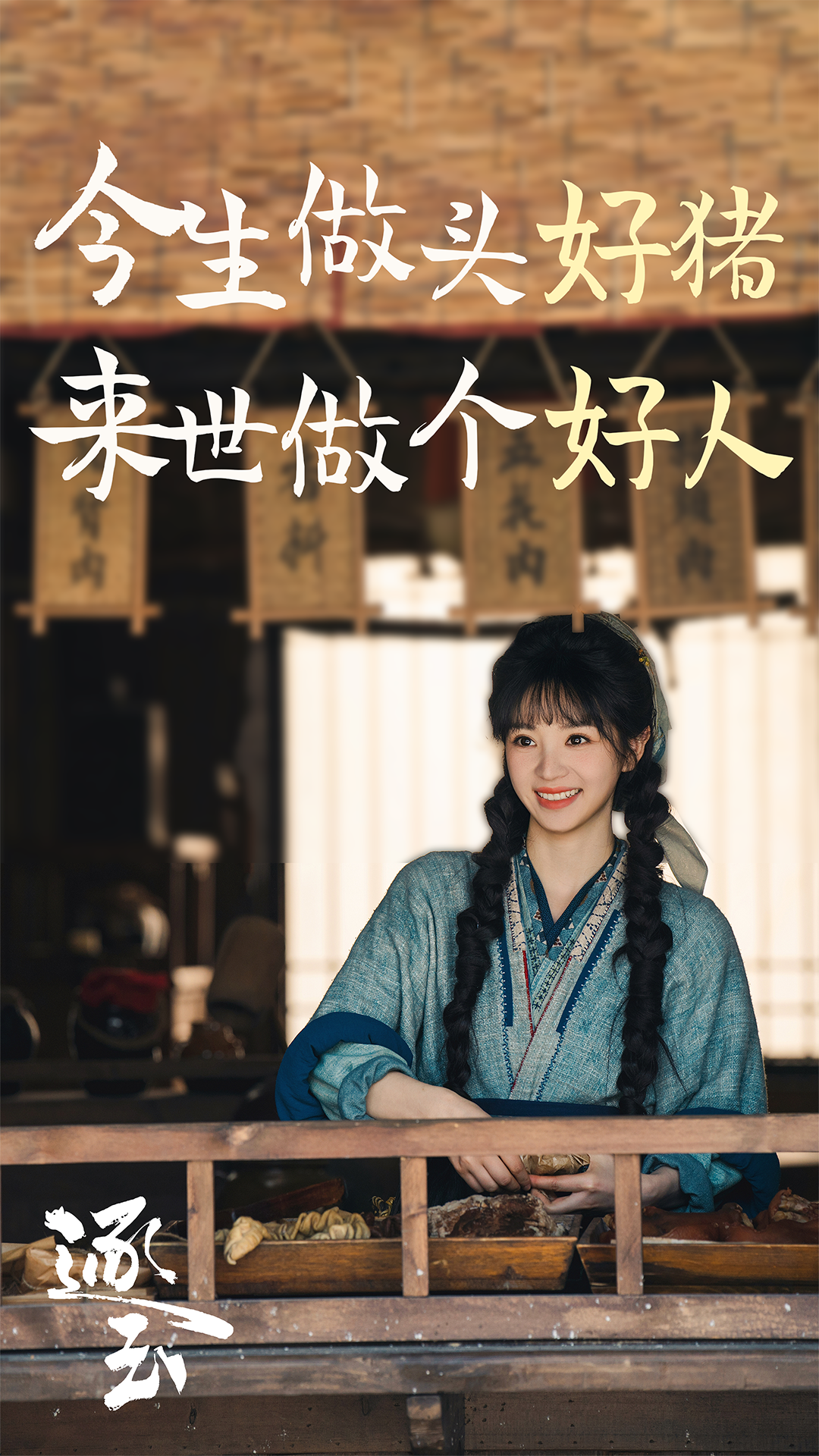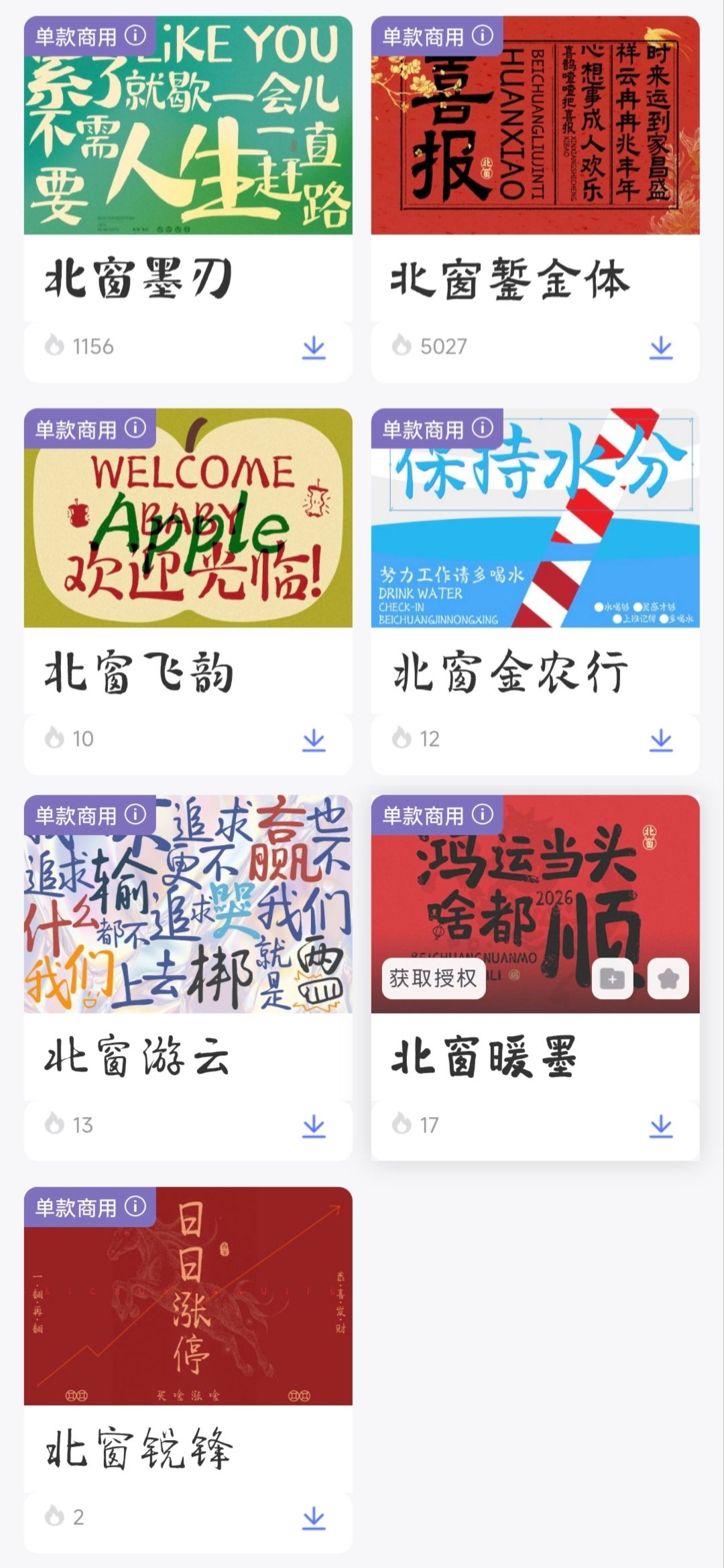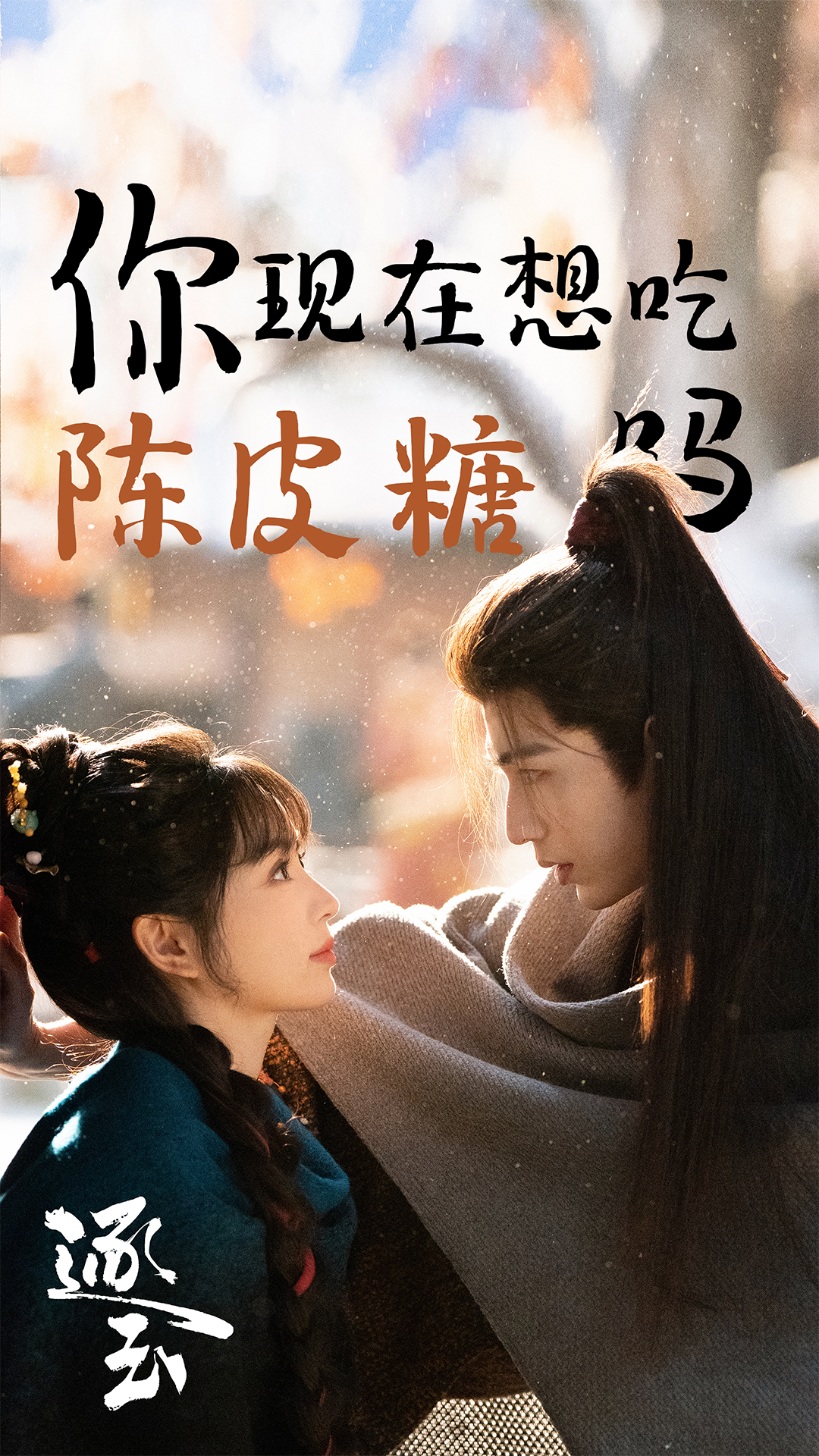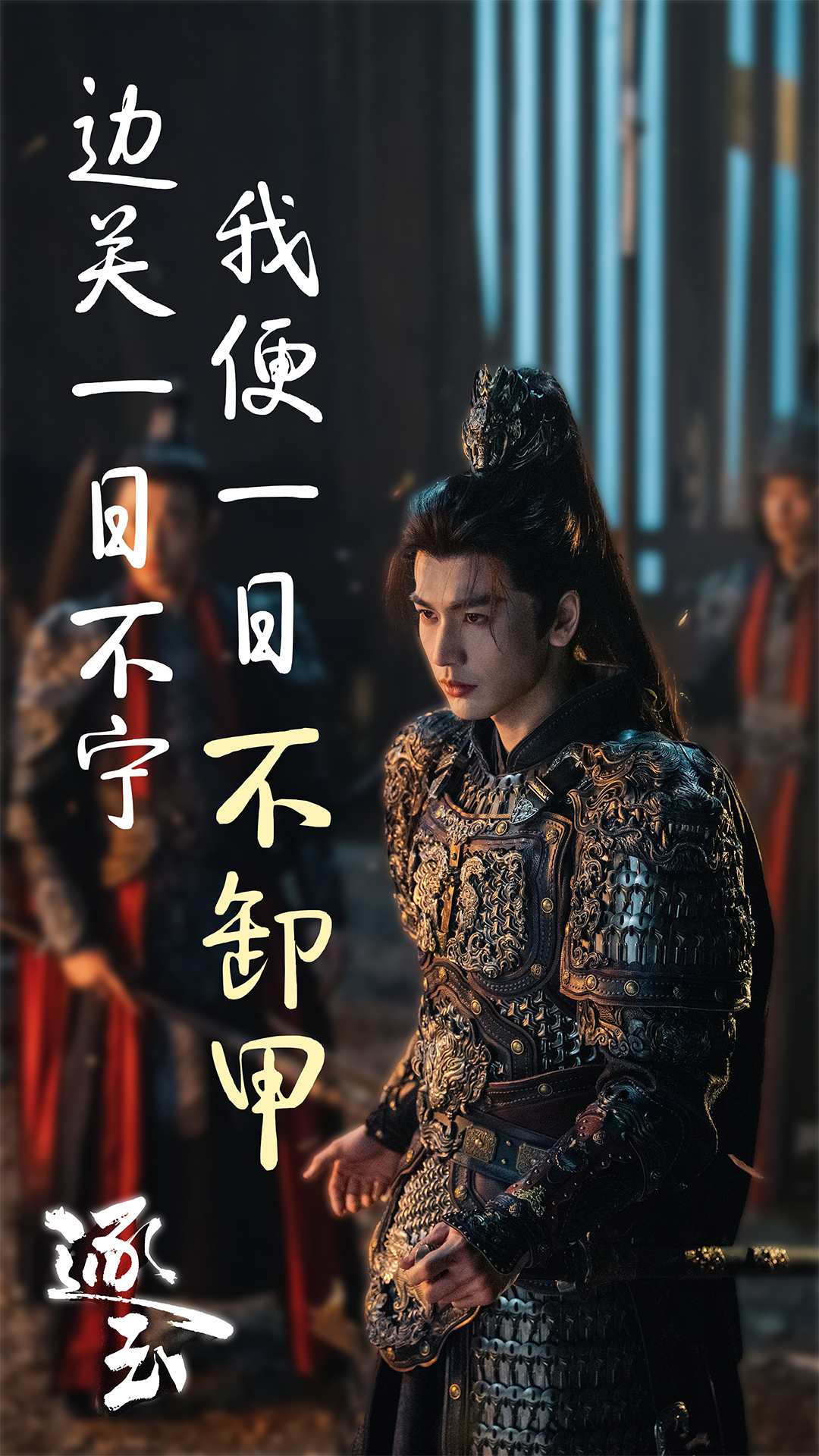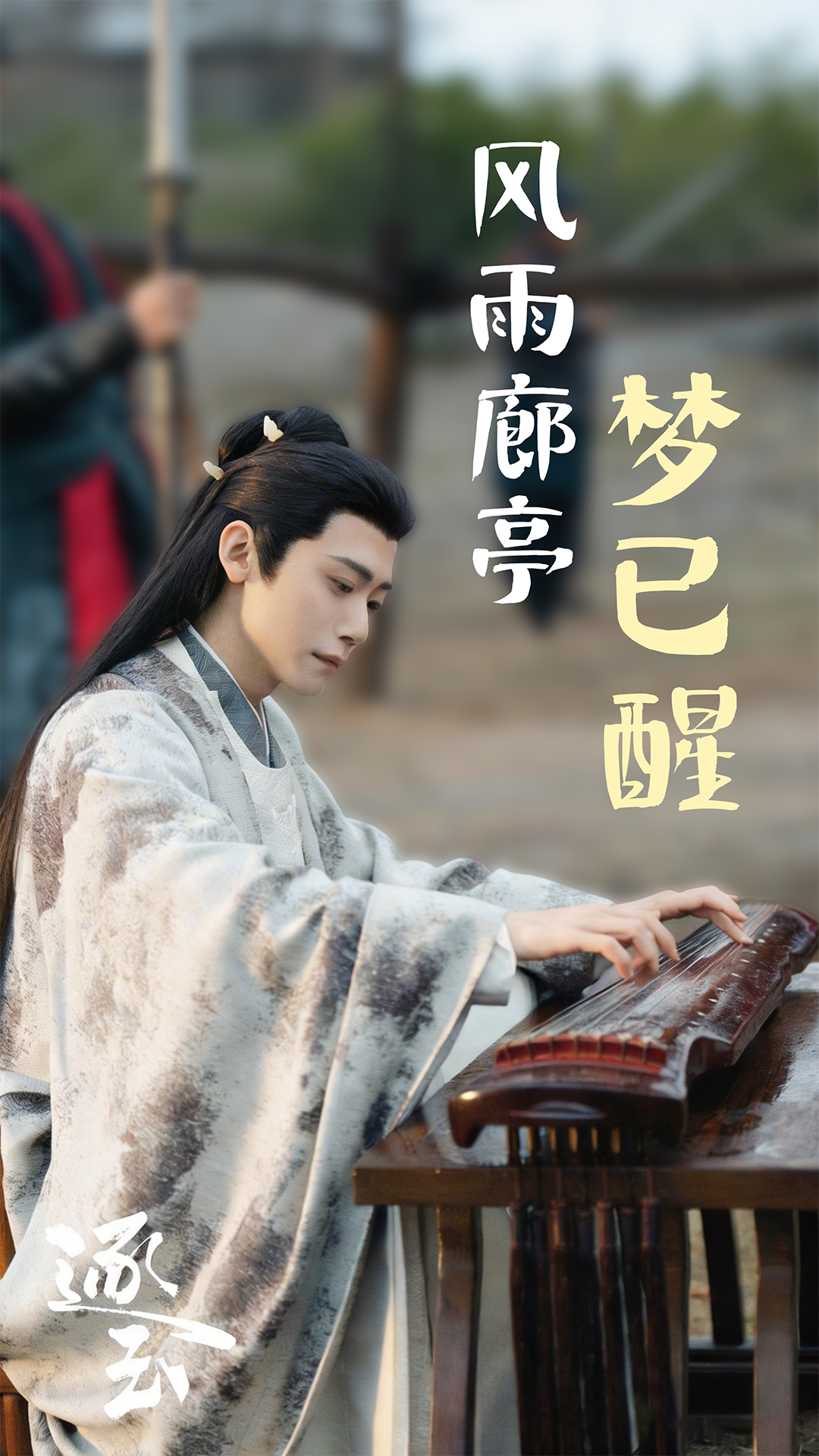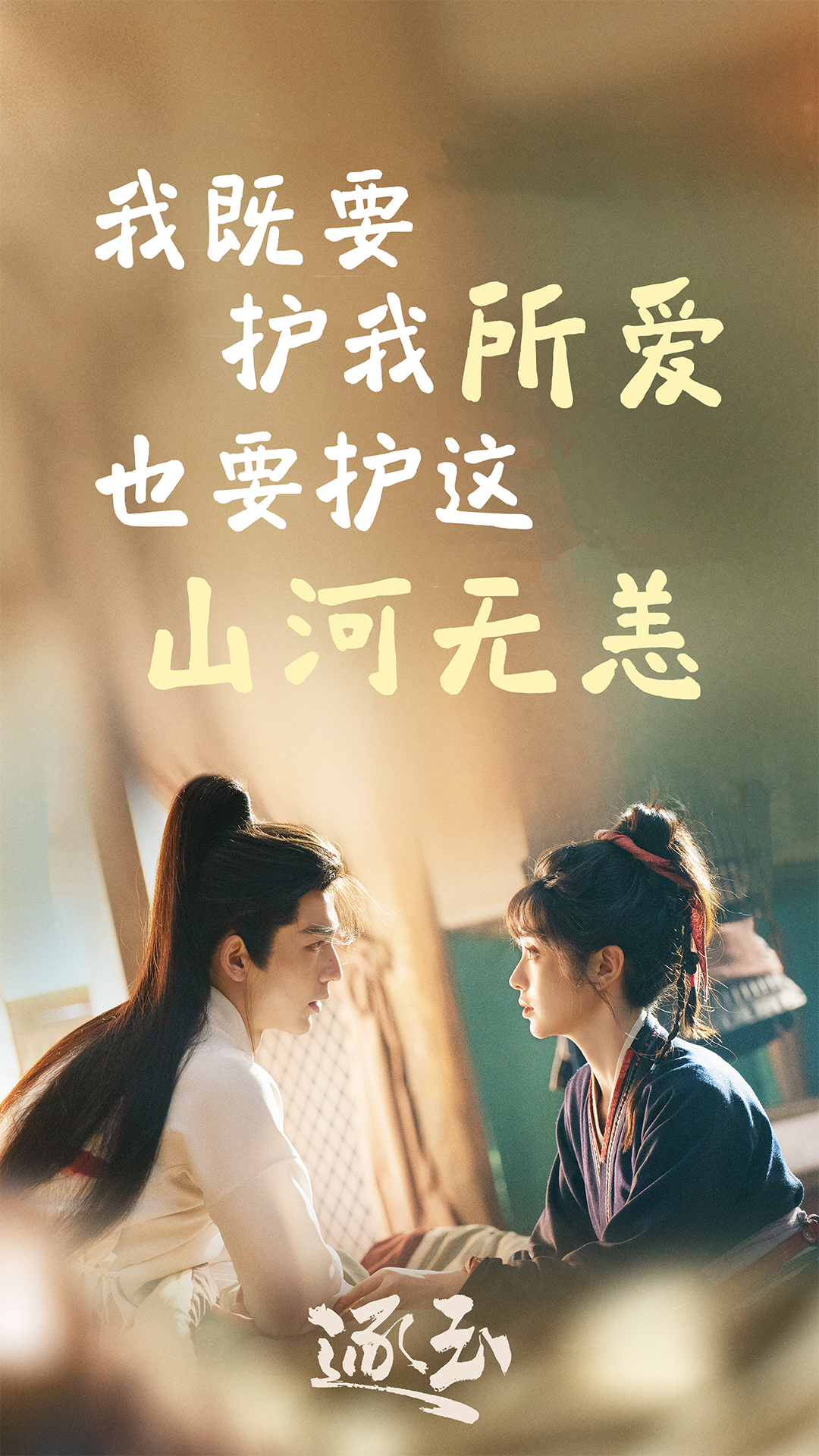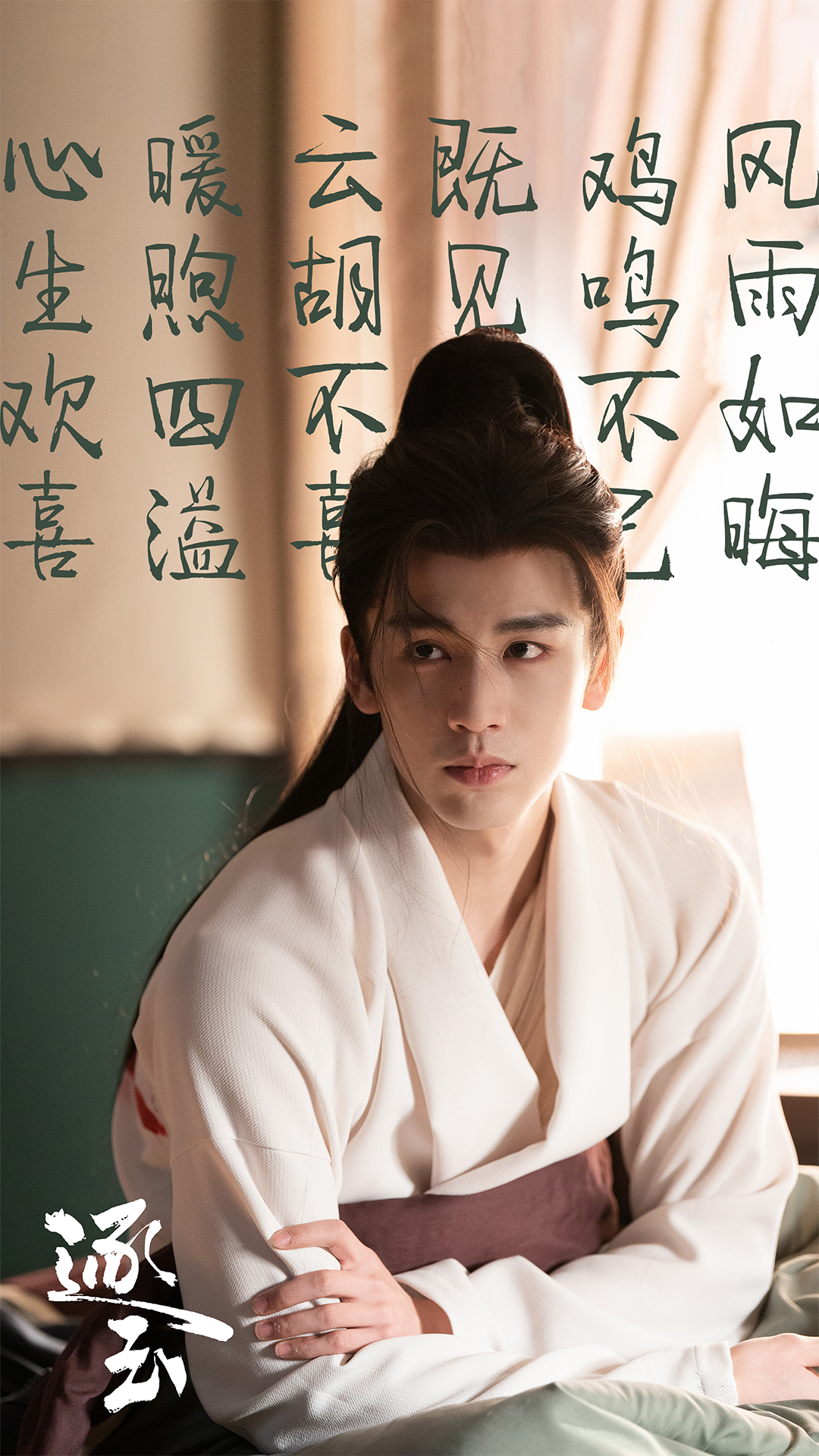
用一句话证明你看过《逐玉》
2026年,表白时我们不说“我喜欢你”,要说“我杀猪养你”;失恋了我们不说“我失恋了”,要说“风雨廊亭梦已醒”……
随着《逐玉》热播,除了男帅女美的画面,还造就了许多剧粉看了会心一笑的名台词梗。
与古偶最配的自然还得是手写书法字体啦!恰逢最近入驻了一个全新的字库品牌——北窗书房,他们将传统书法笔意与现代设计语言融合,目前已上线7款超好看的字体。
柚子也试着把《逐玉》里的出圈台词与这些字体搭配在一起做成了台词海报,当热剧名场面,遇上会“说话”的字体,你猜有多绝?
一、北窗金农行
二、北窗飞韵
三、北窗錾金体
四、北窗游云
五、北窗暖墨
六、北窗墨刃
七、北窗锐锋